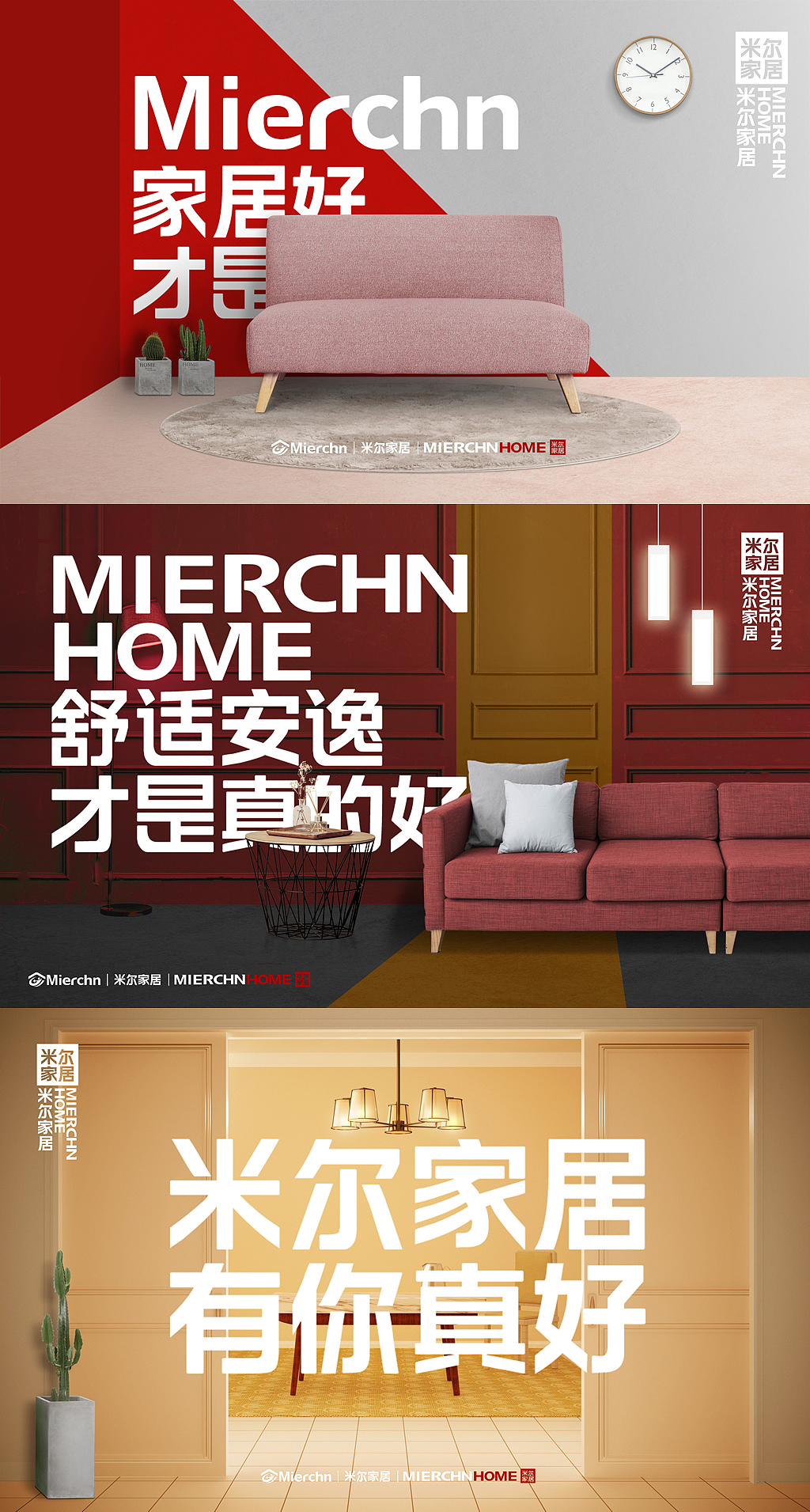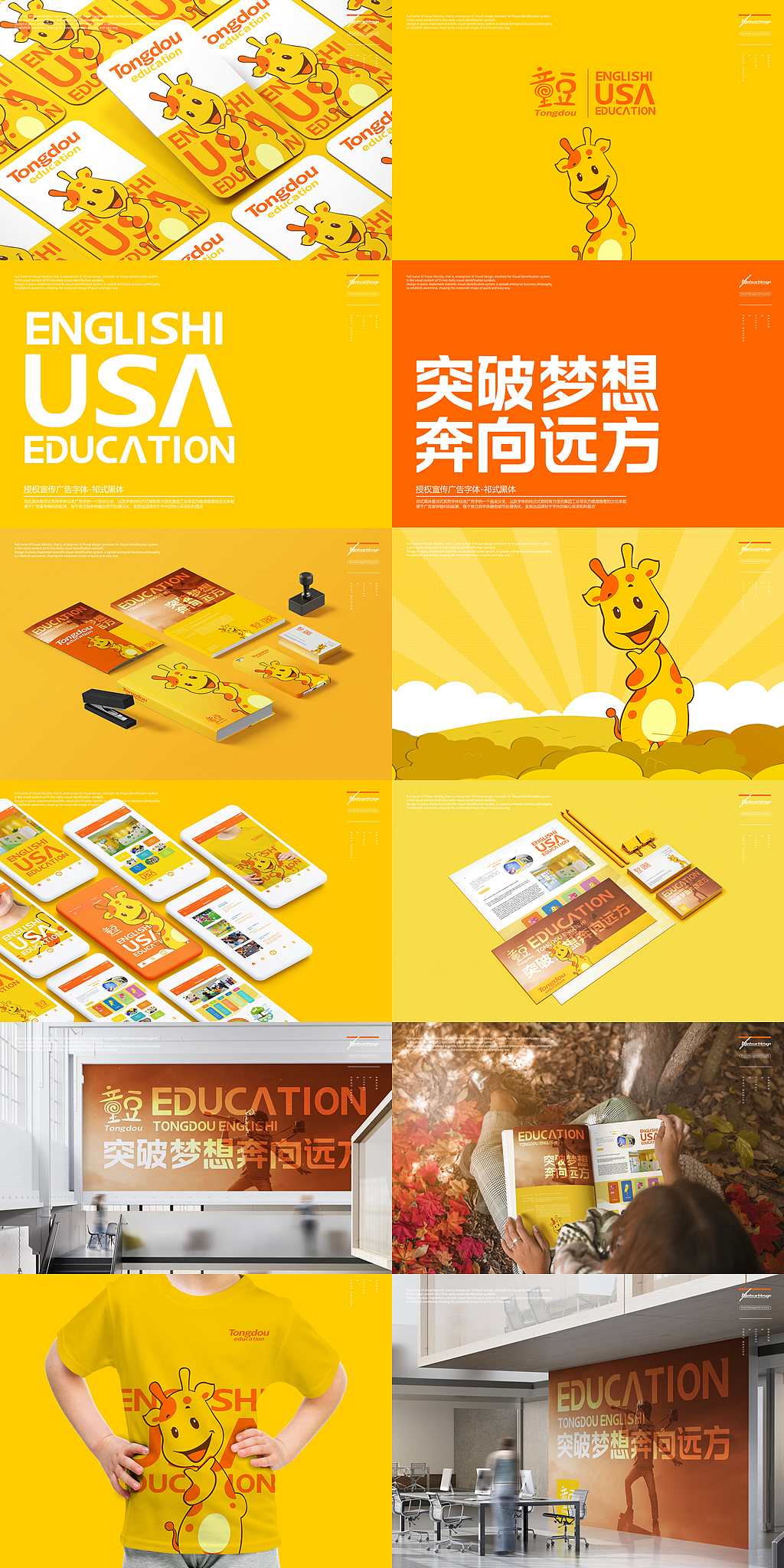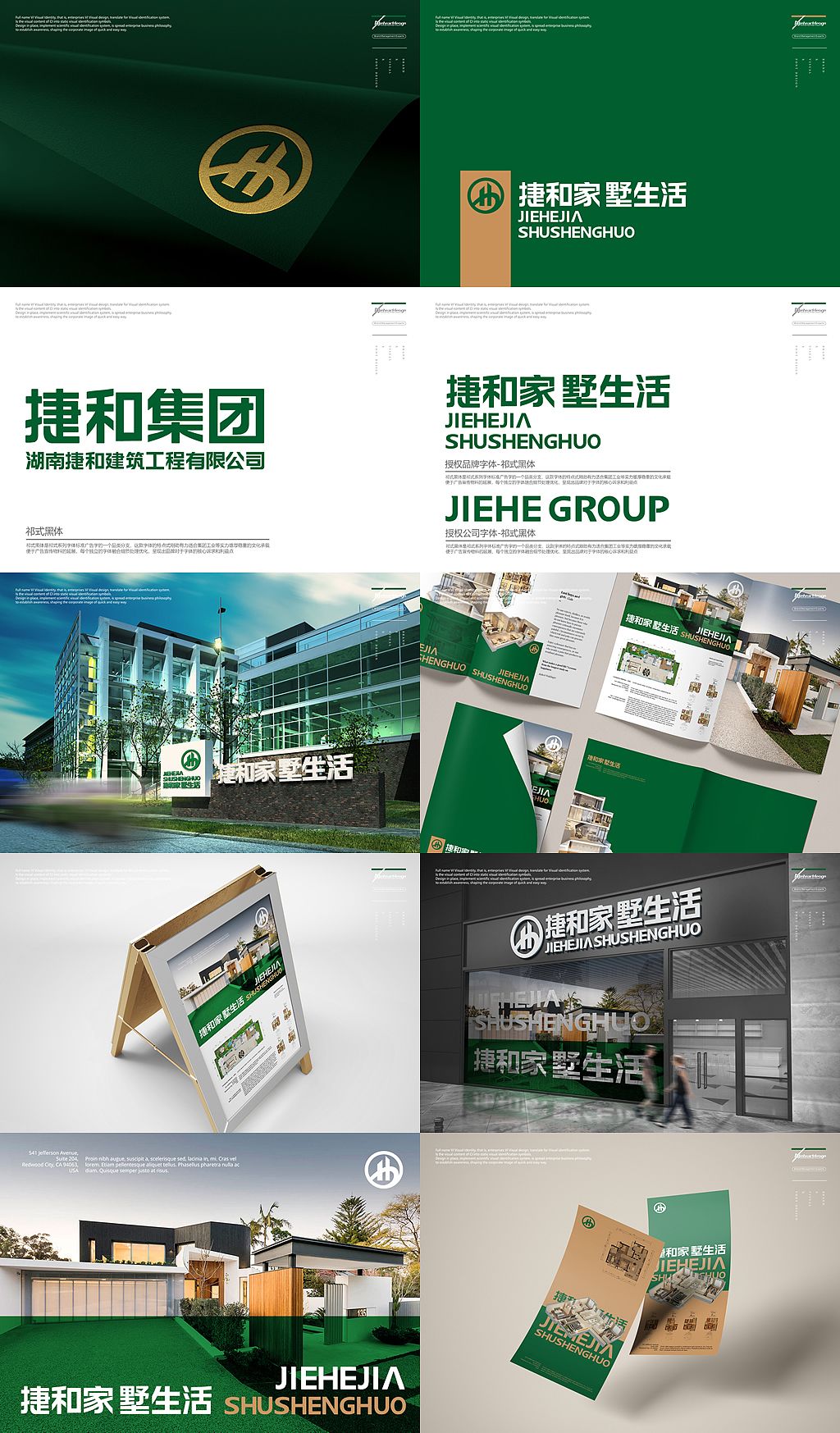
祁式黑体QSHT/FONTS
这套字库是从2015-2020,历时5年,断断续续在不断设计及使用的过程中,结合自身客户,从市场出发边制作边完善整体字库;
其中包括 中文简繁 + 拉丁字符 共7015字的字库;
字体介绍
祁式黑体是祁式系列字体标准广告字的一个品类分支,这款字体的特点式刚劲有力适合集团工业等实力雄厚稳重的文化承载
便于广告宣传物料的延展,每个独立的字体融合细节处理优化,呈现出品牌对于字体的核心诉求和利益点